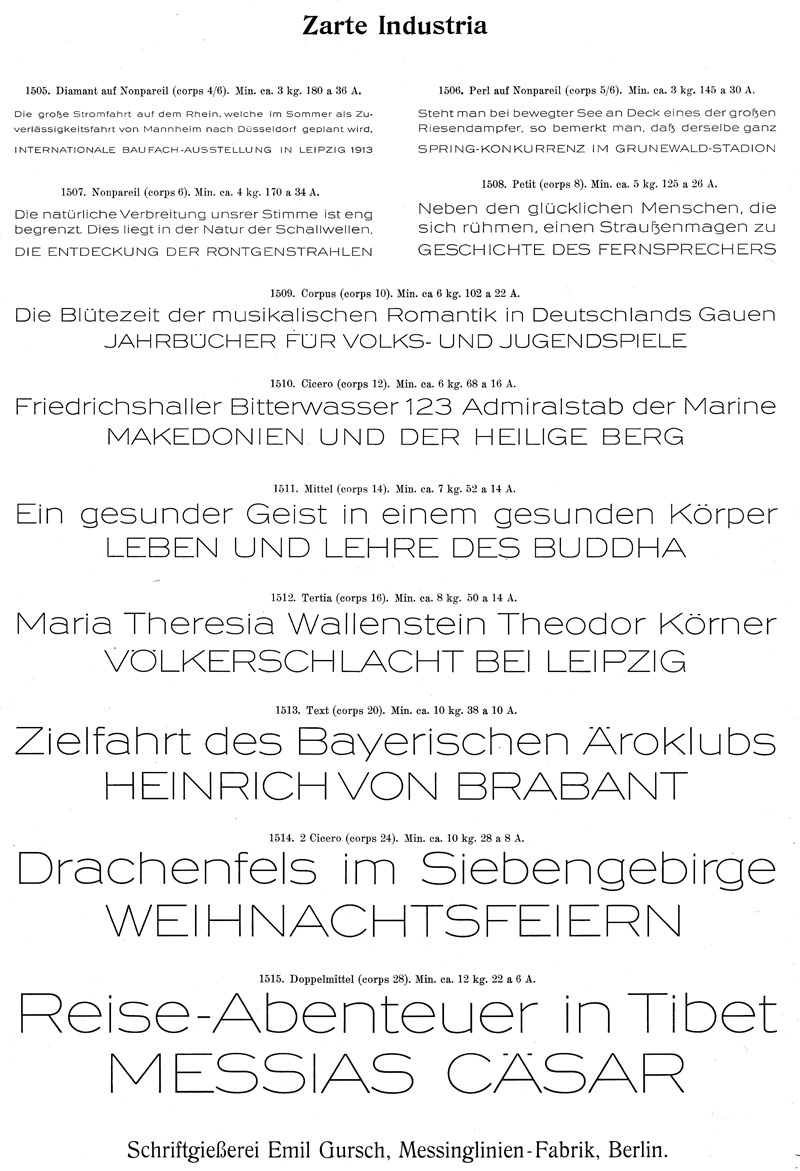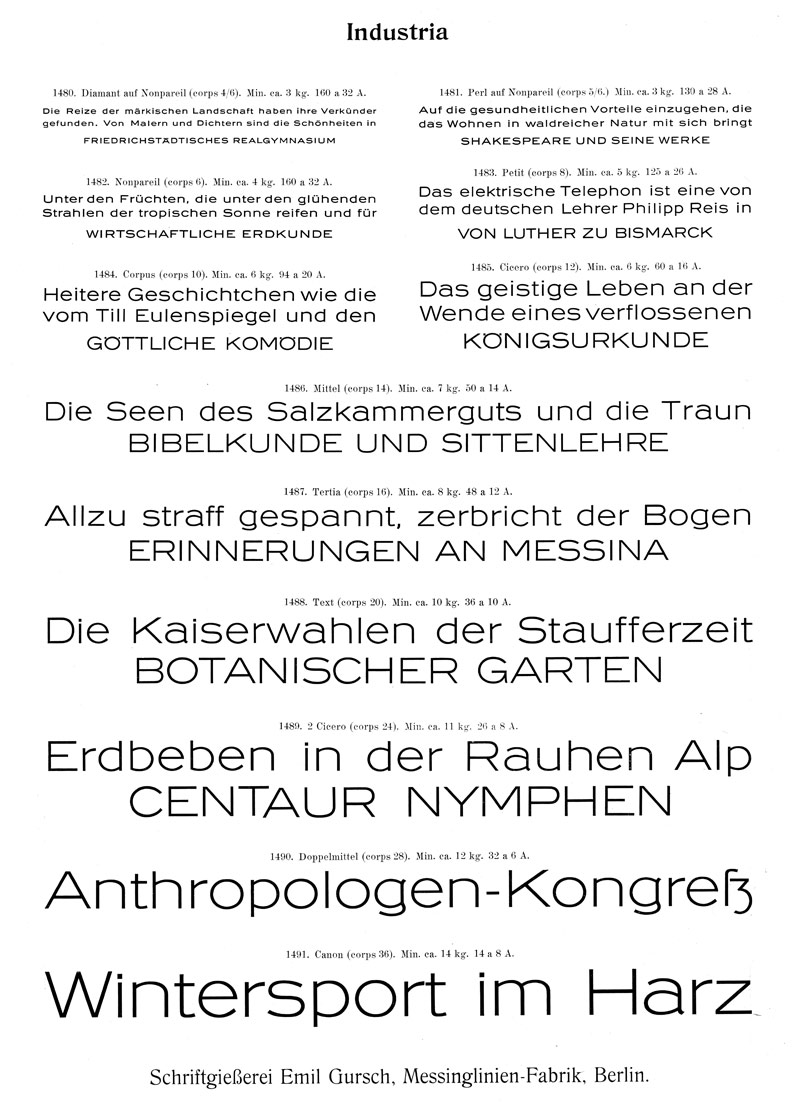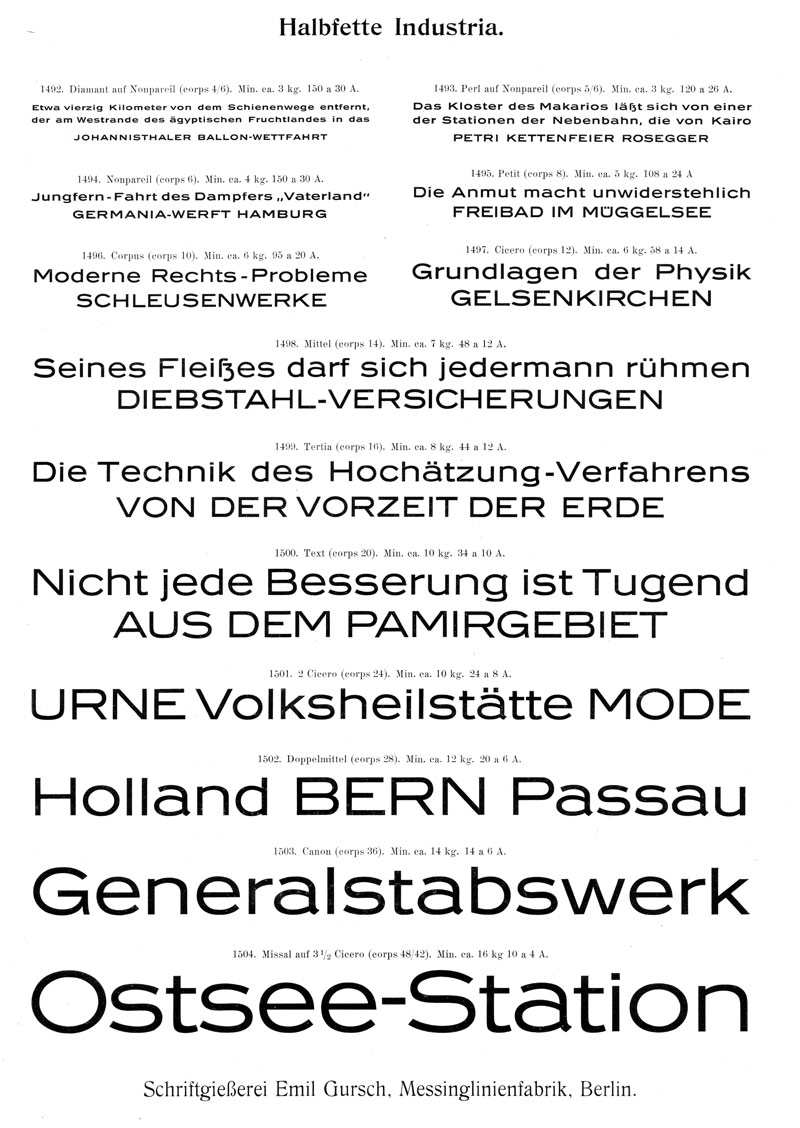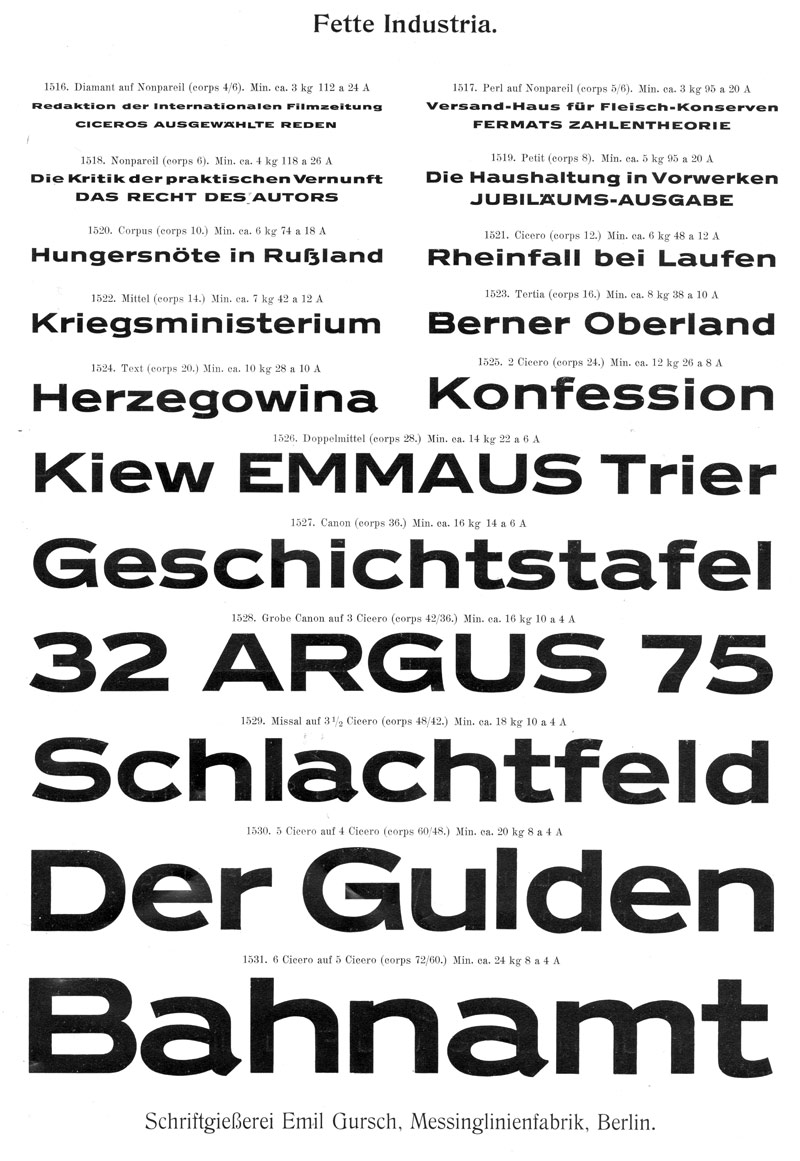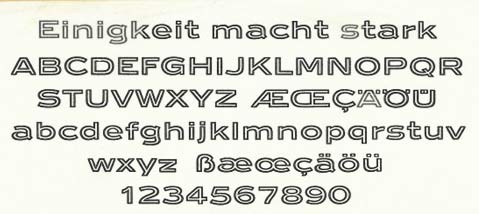
»Industria« digitalisiert?
Immer nur die Extrempunkte mit Ankerpunkten versehen! Die markierten Ankerpunkte sollte alle rausfliegen.
Unter dem Namen »Industria« kannst Du sie jedenfalls nicht herausbringen, den hat sich inzwischen Adobe für eine andere Schrift gekrallt.
Gut zu wissen. Ich hab an »Zehnpfundt-Grotesk« gedacht. Das klingt doch richtig schön nach altem Blei ... :)
Es wäre also möglich, dass Gestalter X eine Schrift von Gestalter Y im Fonteditor seiner Wahl öffnet, zwei Punkte um 1UPM verschiebt und das ganze dann unter neuem Namen herausbringt?
Wenn es sich um einen als Geschmacksmuster geschützten Entwurf handelte, könnte man wohl erfolgreich dagegen vorgehen.
Jens
Schrift öffnen, verändern, speichern und als eigenes verkaufen: Ist die Frage, ob er die Font-Software verändern darf. Das ist in der EULA eines Fonts festgelegt (oder auch nicht).
Zumindest in Softwareprodukten heißt es meistens explizit dass die Software nicht verändert werden darf.
dass schriften grundsätzlich nicht durch copyright geschützt werden können, ist eine US-spezialität. in vor-digitalen zeiten konnten nur die schriftnamen geschützt werden, klone wurden deshalb einfach unter anderen namen herausgebracht. digitale schriften können als software verkauft und geschützt werden.
in EU war das früher ähnlich, heute können schriften hier grundsätzlich wie andere „eigentümliche schöpfungen“ durch das urheberrecht geschützt sein. die eigentümlichkeit kann aber sicher zur streitfrage werden.
das verändern einzelner zeichen oder punktkoordinaten führt wohl zu gar nichts. wenn eine schrift als software geschützt ist, verstößt man mit großer wahrscheinlich gegen die nutzungsbedingungen (blöd wären die hersteller, wenn es so einfach wäre, dann könnte ich Photoshop als eigenes produkt verkaufen, wenn ich nur die icons der werkzeugpalette neu zeichne), und ist die schrift urheberrechtlich geschützt, dann braucht man für die veränderung ja erst das bearbeitungsrecht vom urheber.
paß das Design den heutigen Formbedürfnissen an. Die Schrift wird trotzdem noch genügend "Altes" beibehalten.
Und hier noch, da soeben zur Sammlung dazugekommen (danke an you-know-who-you-are) :D , die Schwere und die Gravur.
Ja. Ne? Besser als die Alternates der Fetten ... :shock:
paß das Design den heutigen Formbedürfnissen an. Die Schrift wird trotzdem noch genügend "Altes" beibehalten.